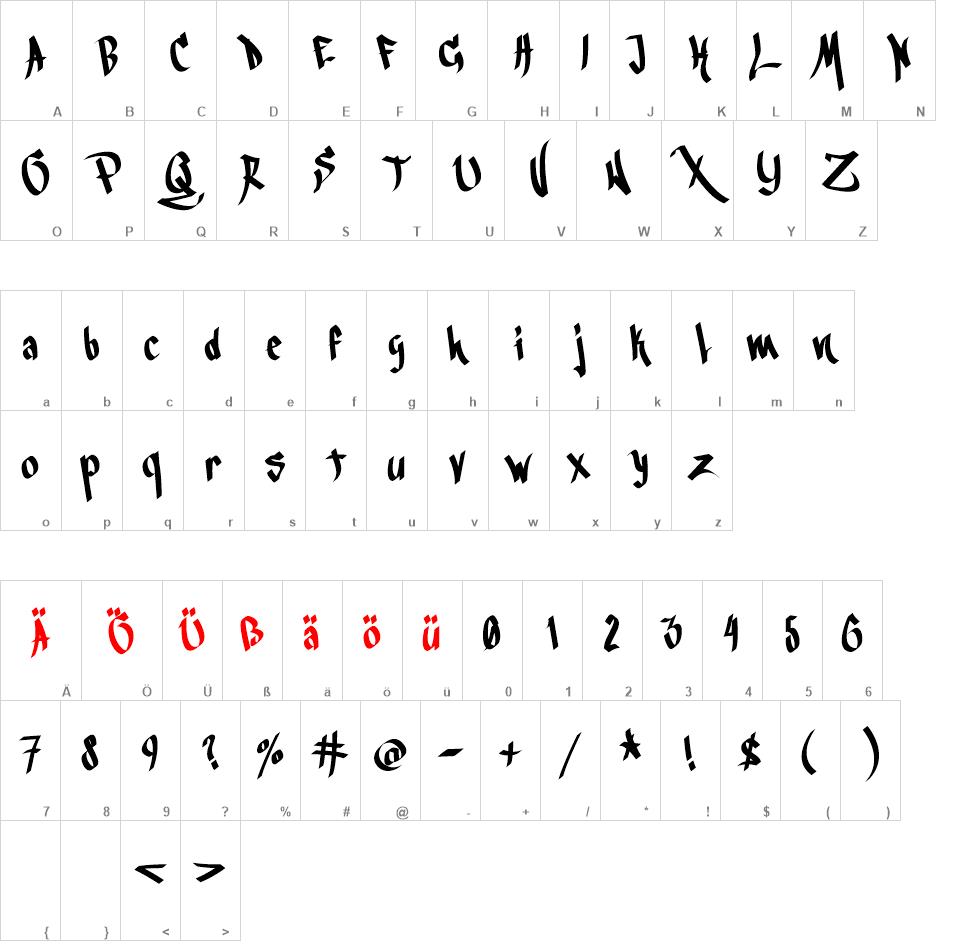
Blackbook 3rd
Blackbook 3rd font
Diese Schrift ist nicht für schwache, faule oder ohnmächtige Menschen gedacht. Es gibt viele großartige Graffiti-Schriften, aber einige können Sie für eine einzelne Schriftfamilie auf über 200 $ bringen. Die Blackbook-Serie ist jedoch völlig kostenlos, genau wie die öffentliche Kunst, die man mühsam an den Wänden rund um die Stadt versprüht.
Blackbook 3rd ist ein riesiger Marker mit fetter Spitze, mit dem Sie nicht in die rechtlichen Schwierigkeiten geraten können, an einer echten Wand zu schreiben. Diese Schriftart muss geschnitten, in der Größe geändert, erodiert und gedehnt werden, um sie an Ihre Graffiti-Designanforderungen anzupassen. Es enthält sogar viele Symbole und fremde Zeichen, damit Sie in Ihrer bevorzugten Sprache aufstehen können.
Diese Schriftart wurde für die Anzeige im kommenden Indiespiel Don't Look Down erstellt.